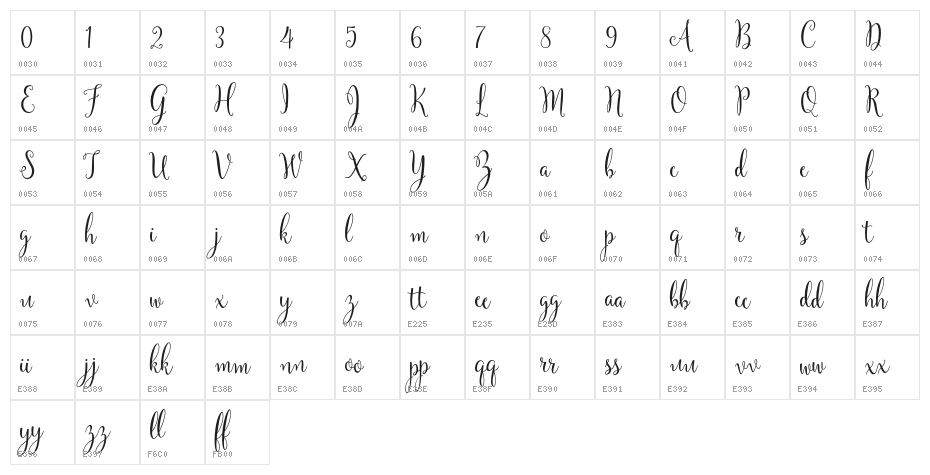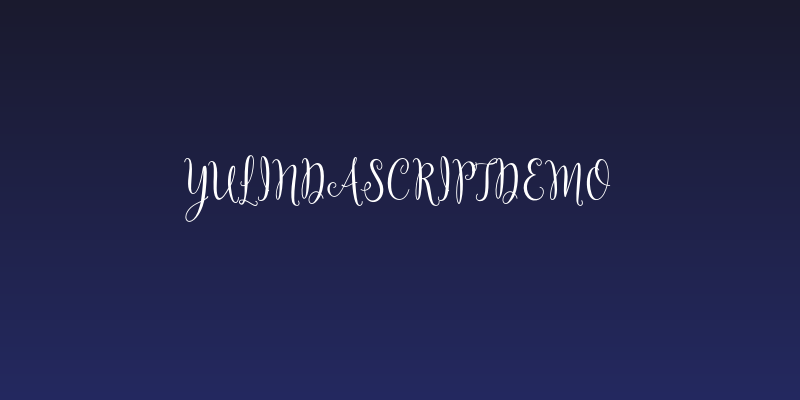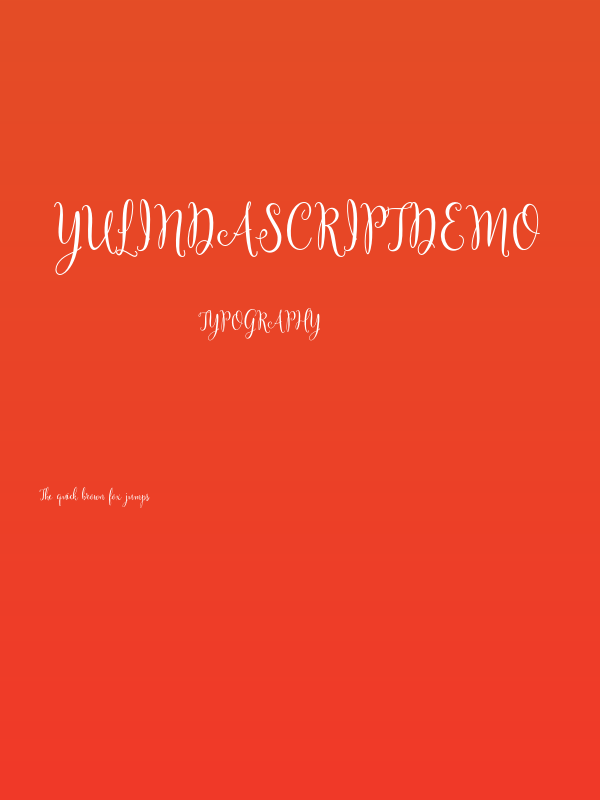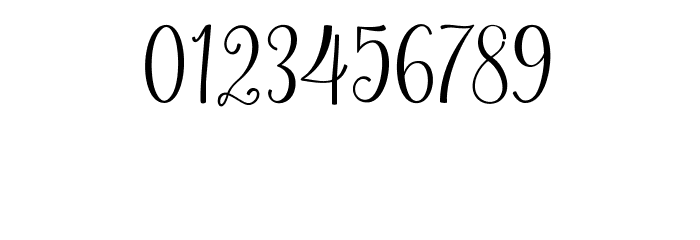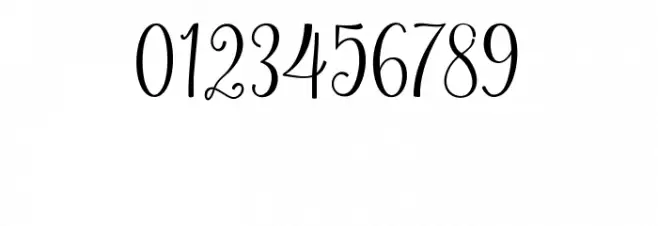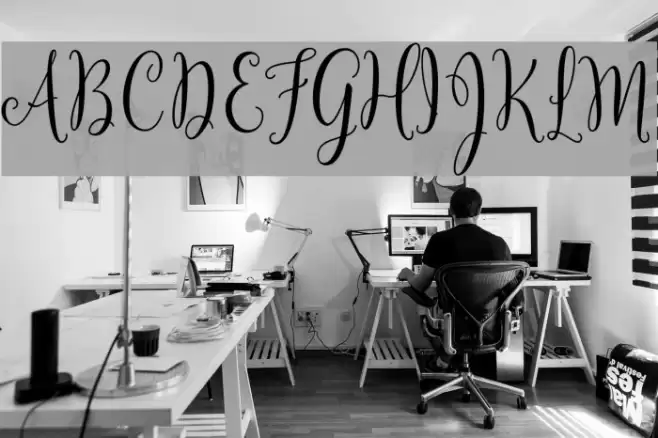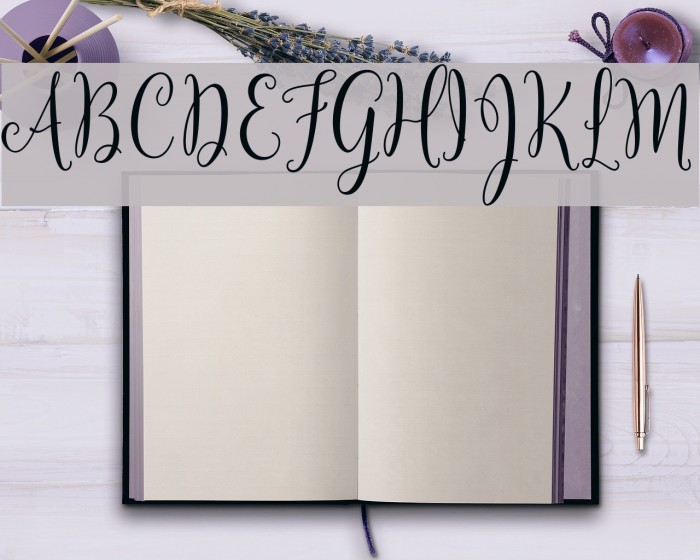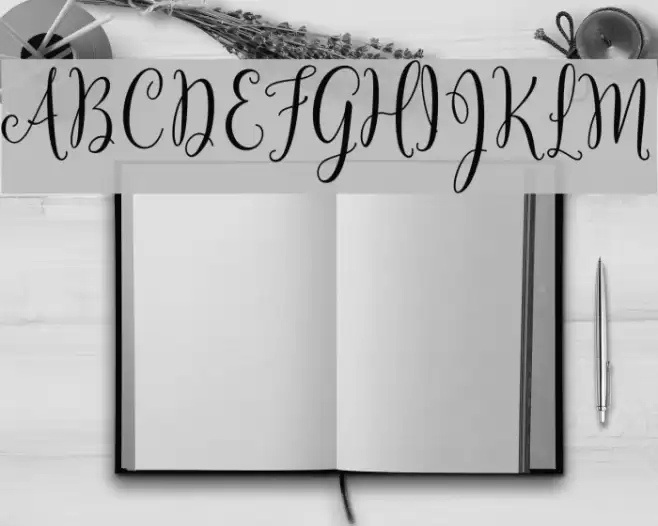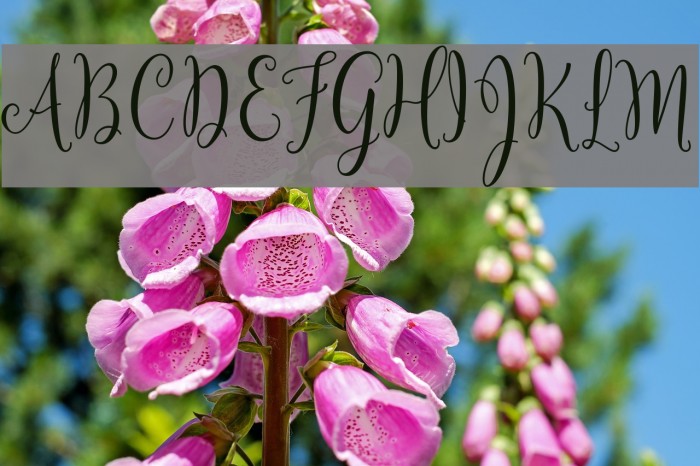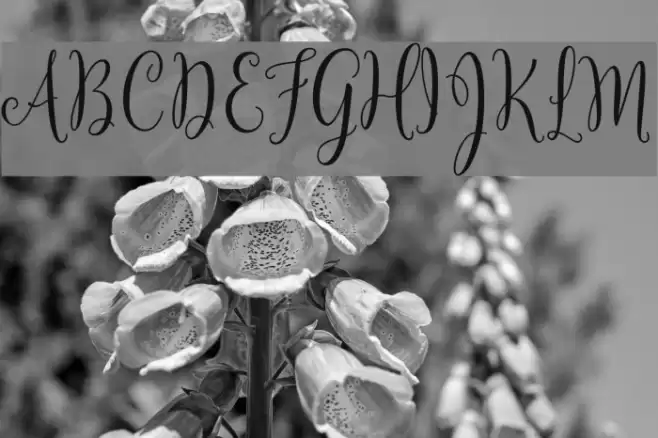
YulindaScriptDemo Font
| 全体的なスタイル | Elegant, Artistic |
| 用途 | Headlines, Logos, Invitations |
| おすすめプロジェクト | Ideal for wedding invitations, branding, decorative headings, and artistic projects. |